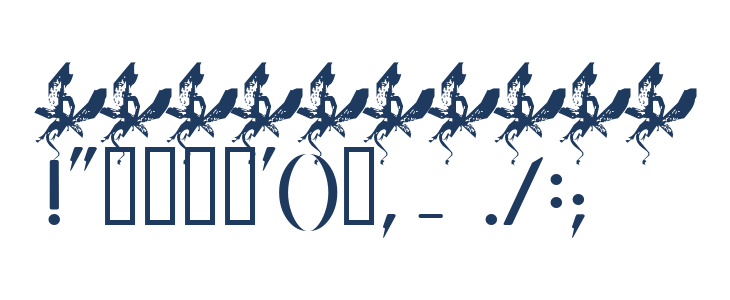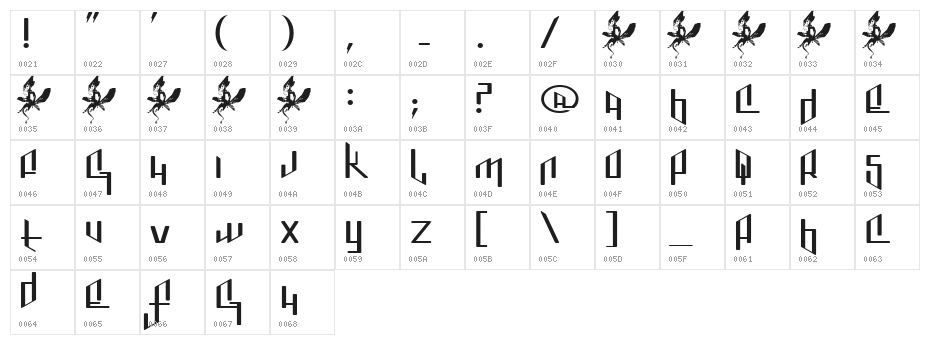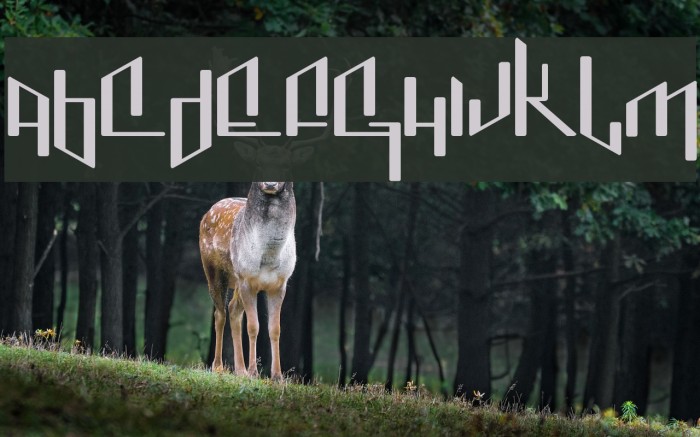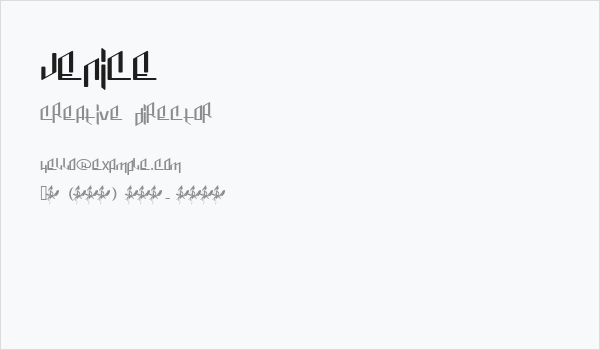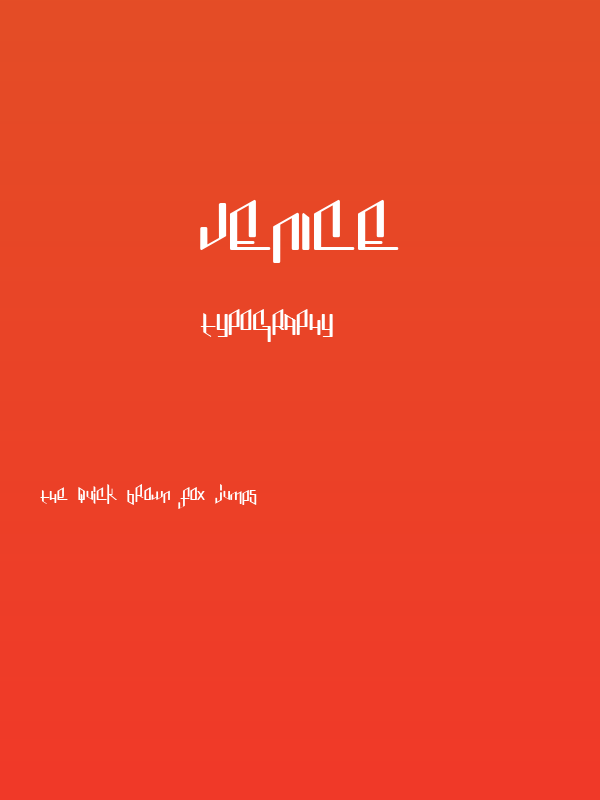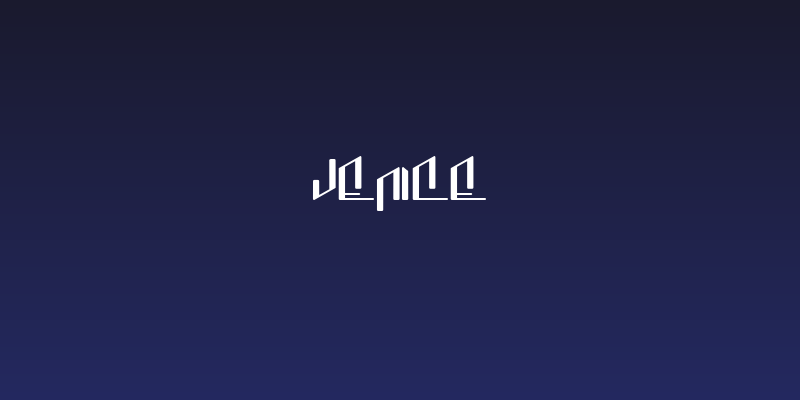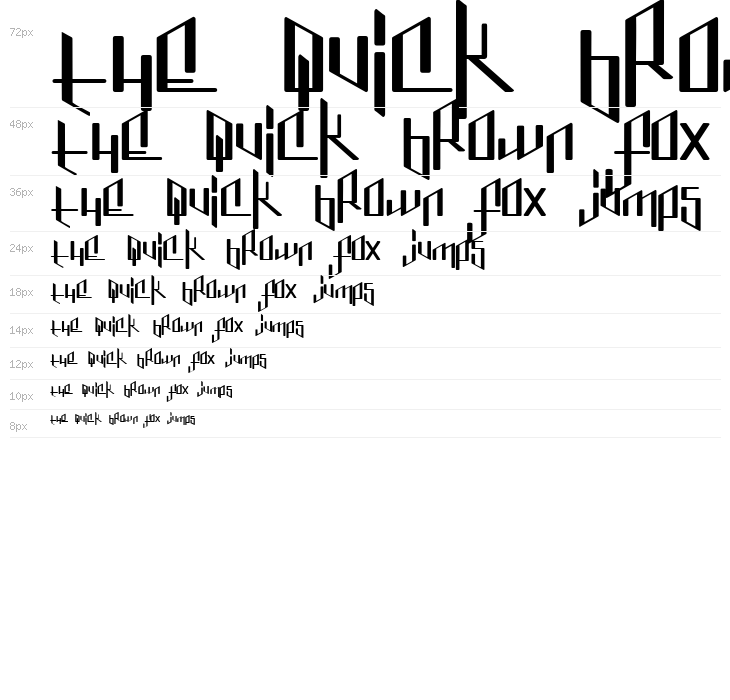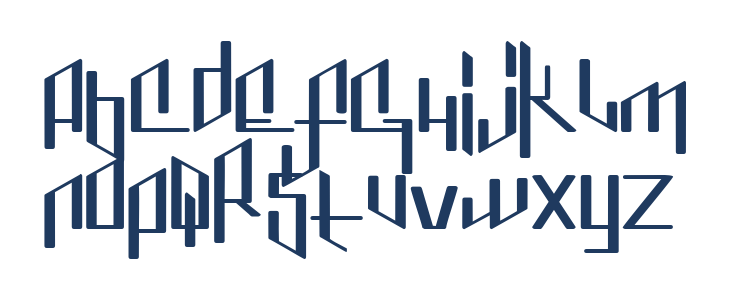
Jenice Font
| Общий стиль | Futuristic, Edgy |
| Рекомендуемые проекты | Ideal for sci-fi themed designs, modern posters, album covers, and branding that requires a bold statement. |